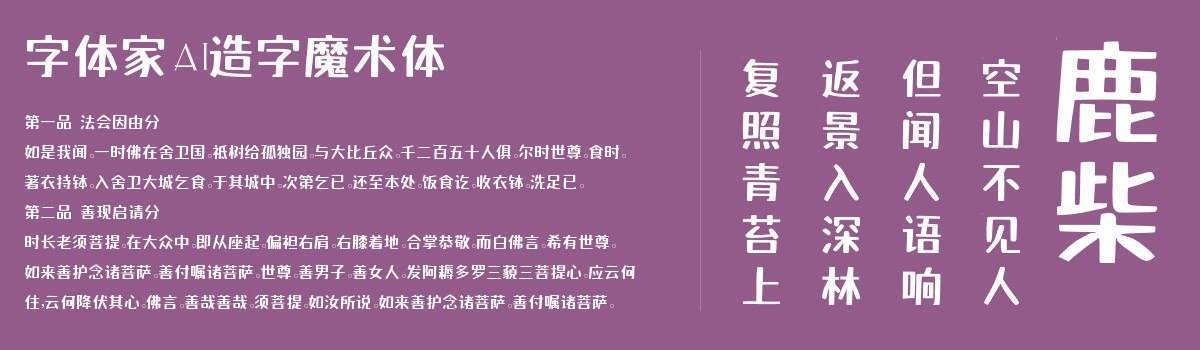
字体家AI造字魔术体
字体家AI造字魔术体是一款由字体家AI神笔造字生成的一款艺术字体,笔画如哑光黑檀木精心裁切,横直竖挺透着利落,转角处似细绒布轻裹出浅弧,不锐不僵。字形方整如稳坐的石墩,重心沉实贴地,笔画像精密拼接的榫卯,粗细均匀无偏颇。摸上去该是平滑无纹,边缘被指尖轻触时能感到极浅的圆融弧度,不硌手却有筋骨。没有多余装饰,却在规整中藏着手工打磨的温润,像被晨露浸过的黑曜石方砖,端庄里透着细腻暖意。比较适合用于艺术类装饰文字,海报、网页、广告设计,室内装饰,平面标题设计、食品包装、品牌标志等。